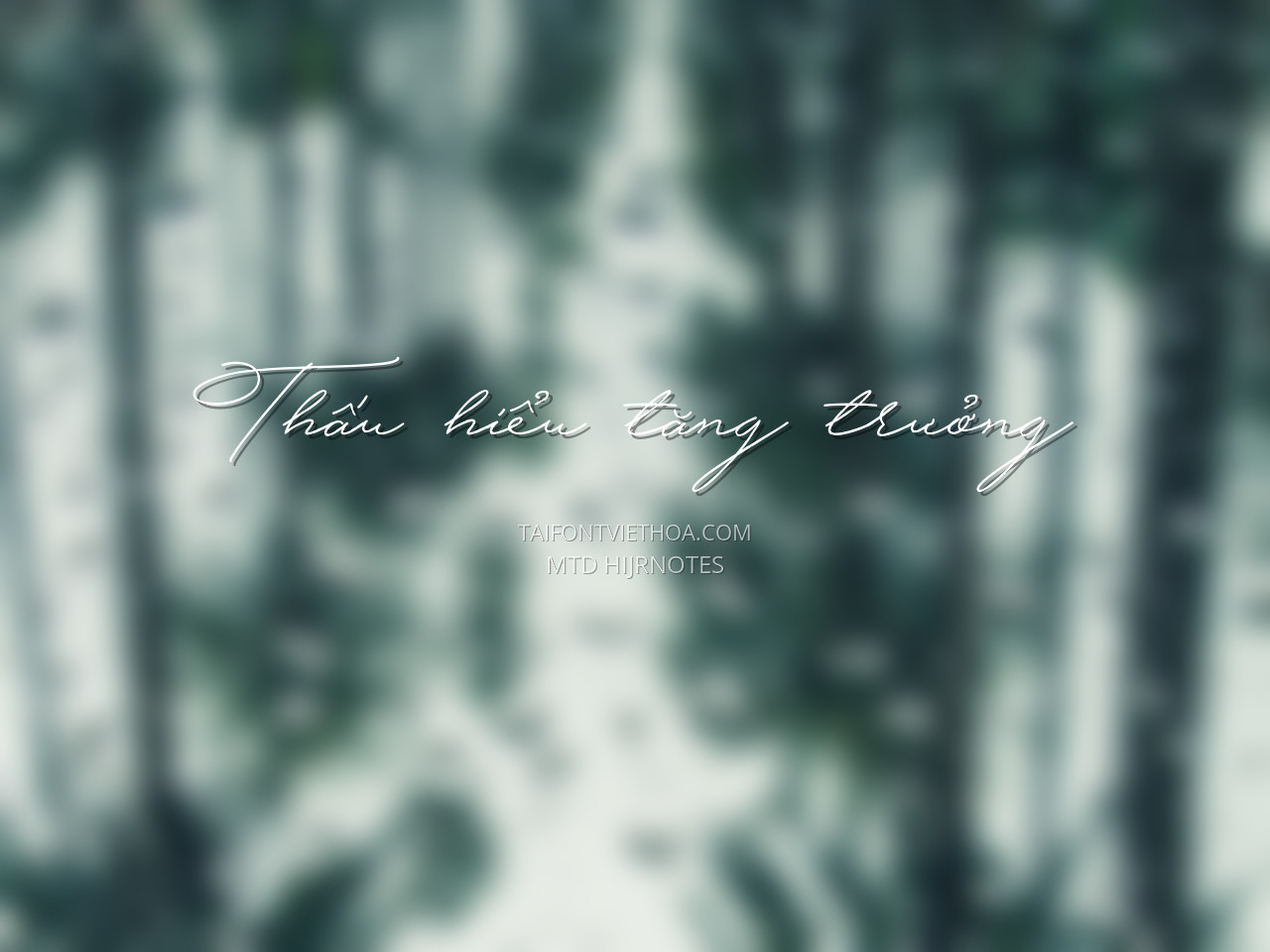
Font việt hóa MTD Hijrnotes
Tác giả Font: Mikrojihad Typography
Giới thiệu về font Hijrnotes
Hijrnotes là một font viết tay tự nhiên (handwritten) mang phong cách ghi chú cá nhân, được thiết kế bởi Motokiwo Type (MTD). Font tái hiện chân thực nét chữ tay đời thường – mộc mạc, gần gũi nhưng vẫn có sự chăm chút trong từng đường nét. Với kiểu dáng gọn gàng, hơi nghiêng và độ đậm vừa phải, Hijrnotes tạo cảm giác thân thiện, nhẹ nhàng nhưng vẫn đủ cá tính để sử dụng trong thiết kế hiện đại. Phiên bản Việt hóa được thực hiện bởi chính MTD, hỗ trợ đầy đủ tiếng Việt và hơn 70 ngôn ngữ khác, đảm bảo khả năng ứng dụng rộng rãi cả trong nước và quốc tế.
Font Hijrnotes được taifontviethoa.com chọn lọc và giới thiệu trong nhóm font viết tay cá nhân, phù hợp với các dự án thiết kế mang phong cách casual, tối giản hoặc giàu cảm xúc cá nhân. Đây là kiểu chữ lý tưởng cho những ai yêu thích sự giản dị nhưng vẫn muốn thể hiện dấu ấn riêng trong từng thiết kế.
Đặc điểm thiết kế và ứng dụng của font Hijrnotes
Hijrnotes có cấu trúc chữ mềm mại, nét chữ đều và các ký tự được sắp xếp với khoảng cách hợp lý. Font mang hơi hướng tự nhiên như những dòng ghi chú viết tay trên sổ tay, phù hợp với phong cách thiết kế nhẹ nhàng, tinh tế hoặc mang hơi hướng đời thường. Bộ font cũng hỗ trợ ligatures và các ký tự đặc biệt, giúp tăng khả năng trình bày linh hoạt.
Ứng dụng lý tưởng: tiêu đề blog, trích dẫn cá nhân, thiệp chúc, bao bì sản phẩm thủ công, thiết kế truyền cảm hứng, bài đăng mạng xã hội, hoặc các thiết kế cần tạo cảm giác gần gũi, thân thiện. Ngành nghề phù hợp: sáng tạo nội dung, giáo dục, lifestyle, quà tặng cá nhân, và các dự án cá nhân hóa giàu tính biểu cảm.